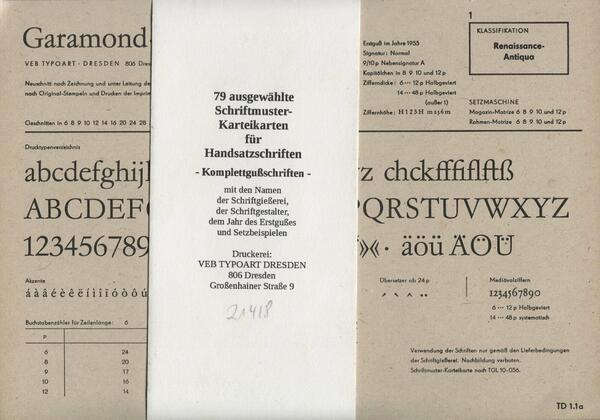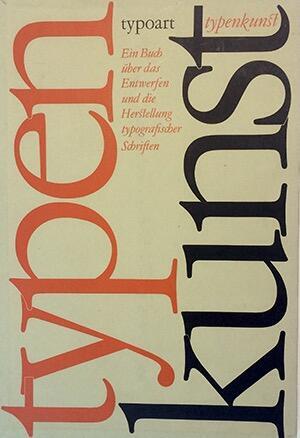
- Land: Deutschland
- Ort: Dresden
- Gegründet: 1951
- Status: nicht mehr aktiv
Der volkseigene Betrieb Typoart war seit 1951 der zentrale Schrifthersteller der DDR. In ihm gingen verschiedene Schriftanbieter (Schriftguß KG Dresden und Schelter & Giesecke/Ludwig Wagner in Leipzig) auf, die im Ostteil des Landes ansässig waren.
Typoart produzierte Hand- und Maschinensatz-Schriften (Linotype/Monotype) und später auch Fotosatzschriften.
Für viele Typoart-Schriften gibt es zeitgemäße Digitalisierungen, teils von verschiedenen Herstellern und teils unter verschiedenen Namen. Die Namensrechte der meisten Typoart-Schriften liegen heute bei Elsner+Flake. Alternative Angebote von Schriften, die auch Typoart im Programm hatte, gibt es unter anderen bei Primetype, RMU, Just Another Foundry, preussType und URW++.